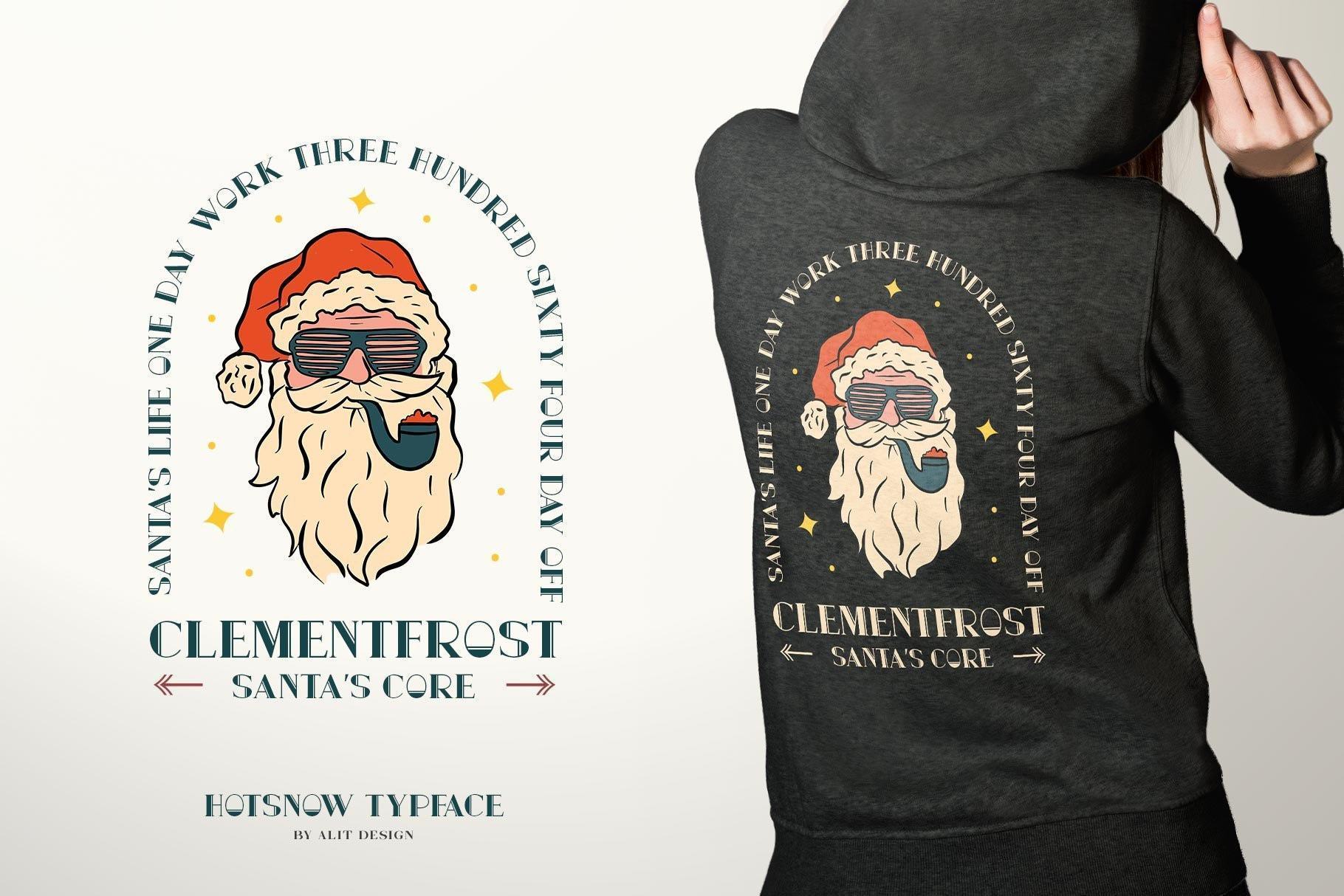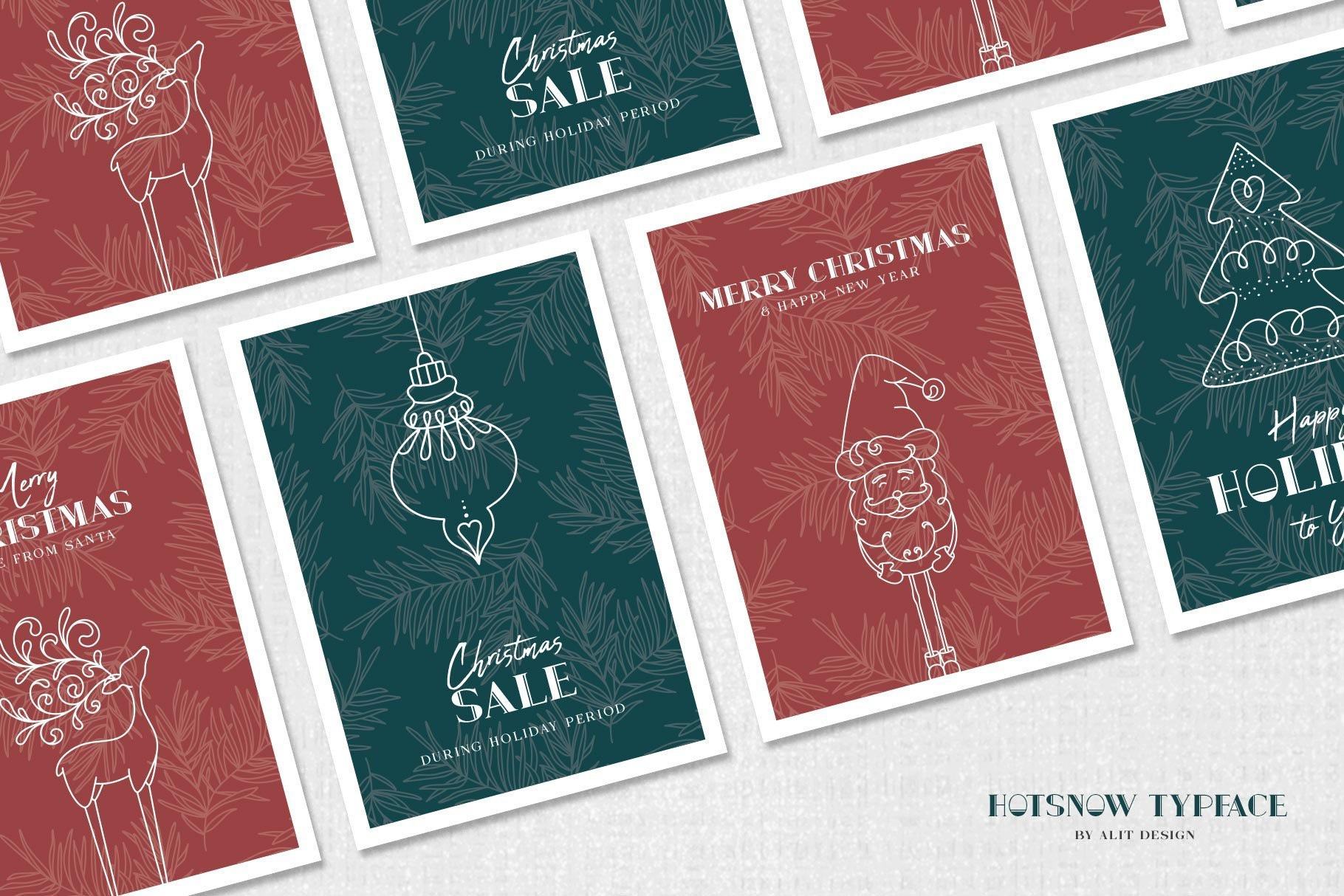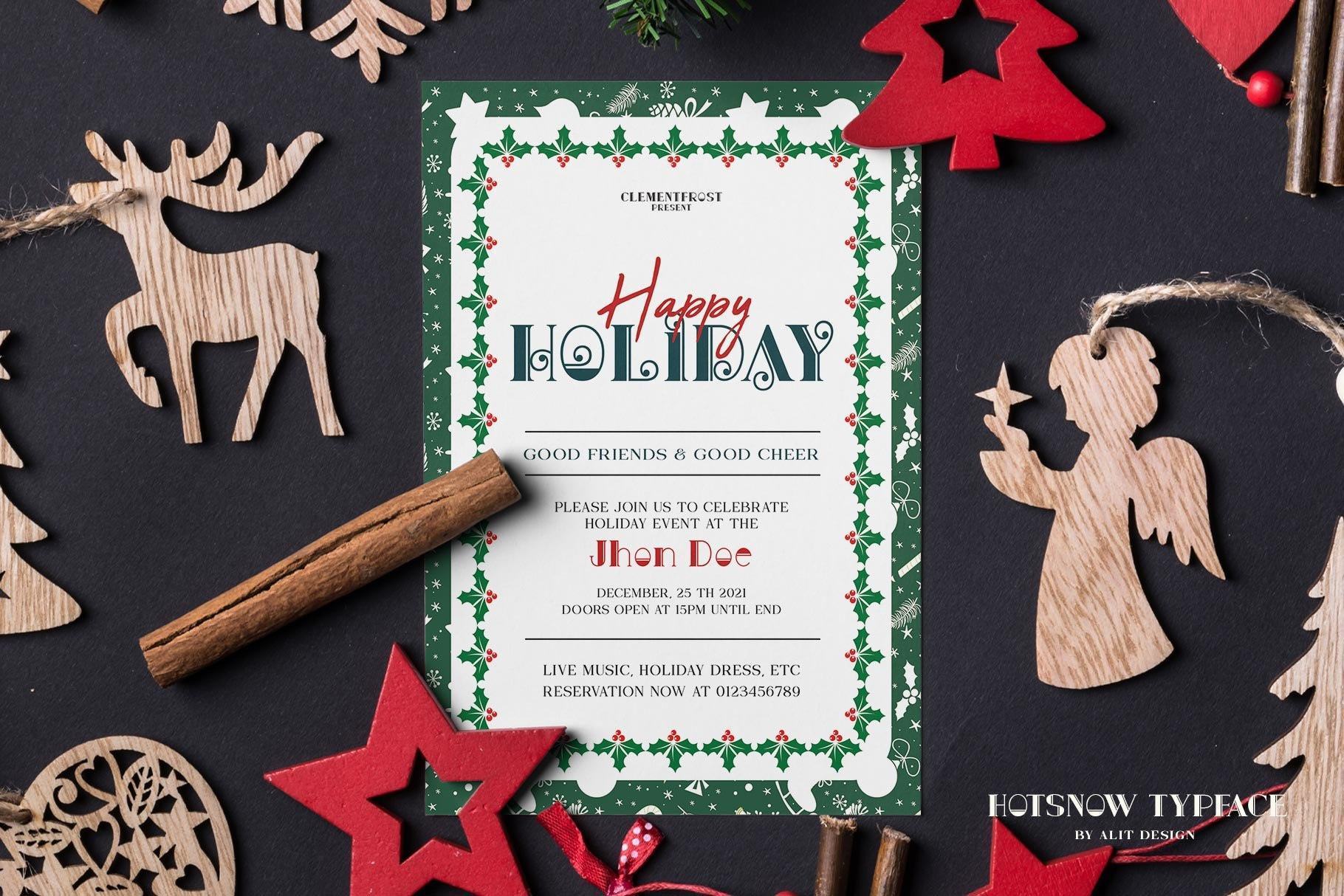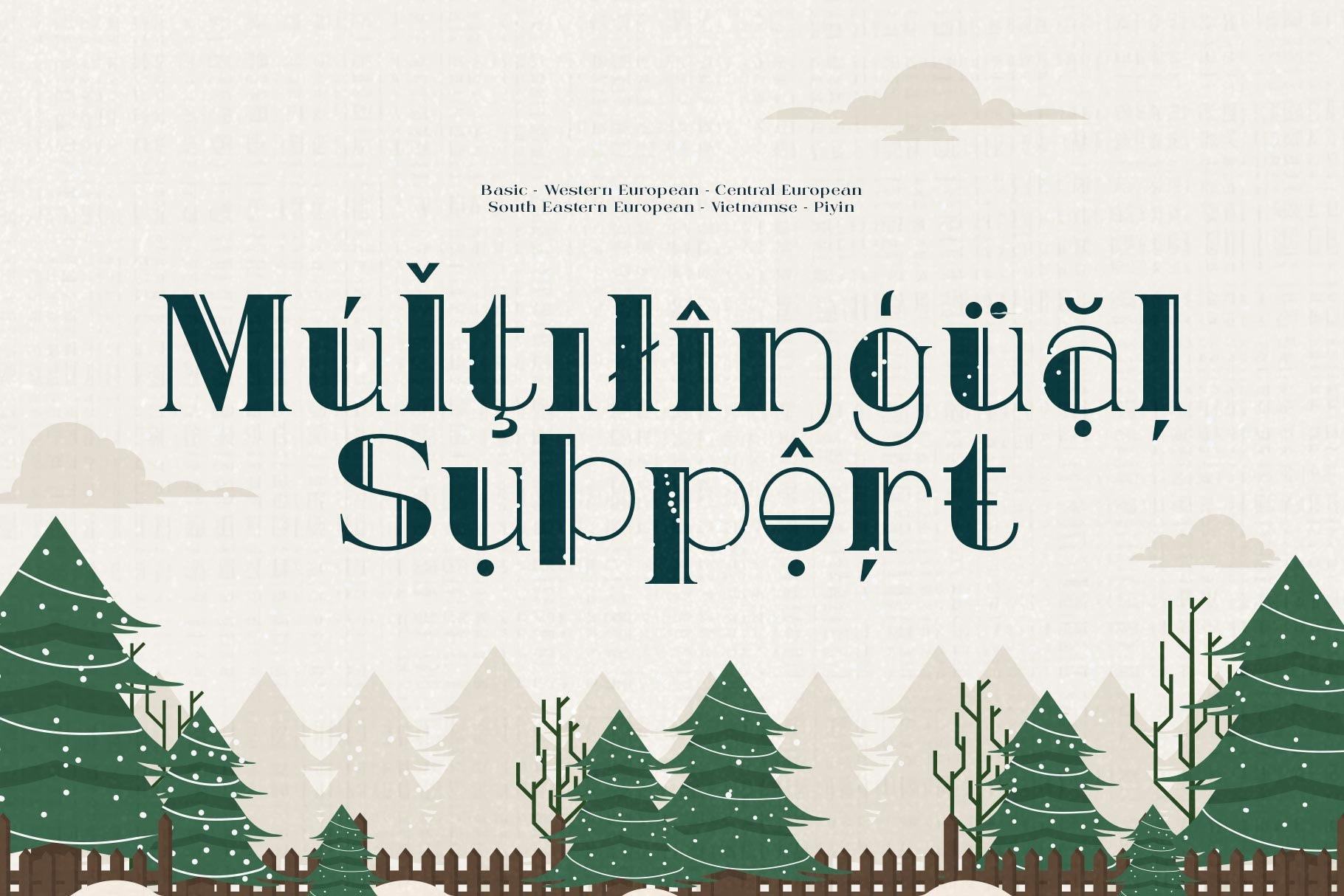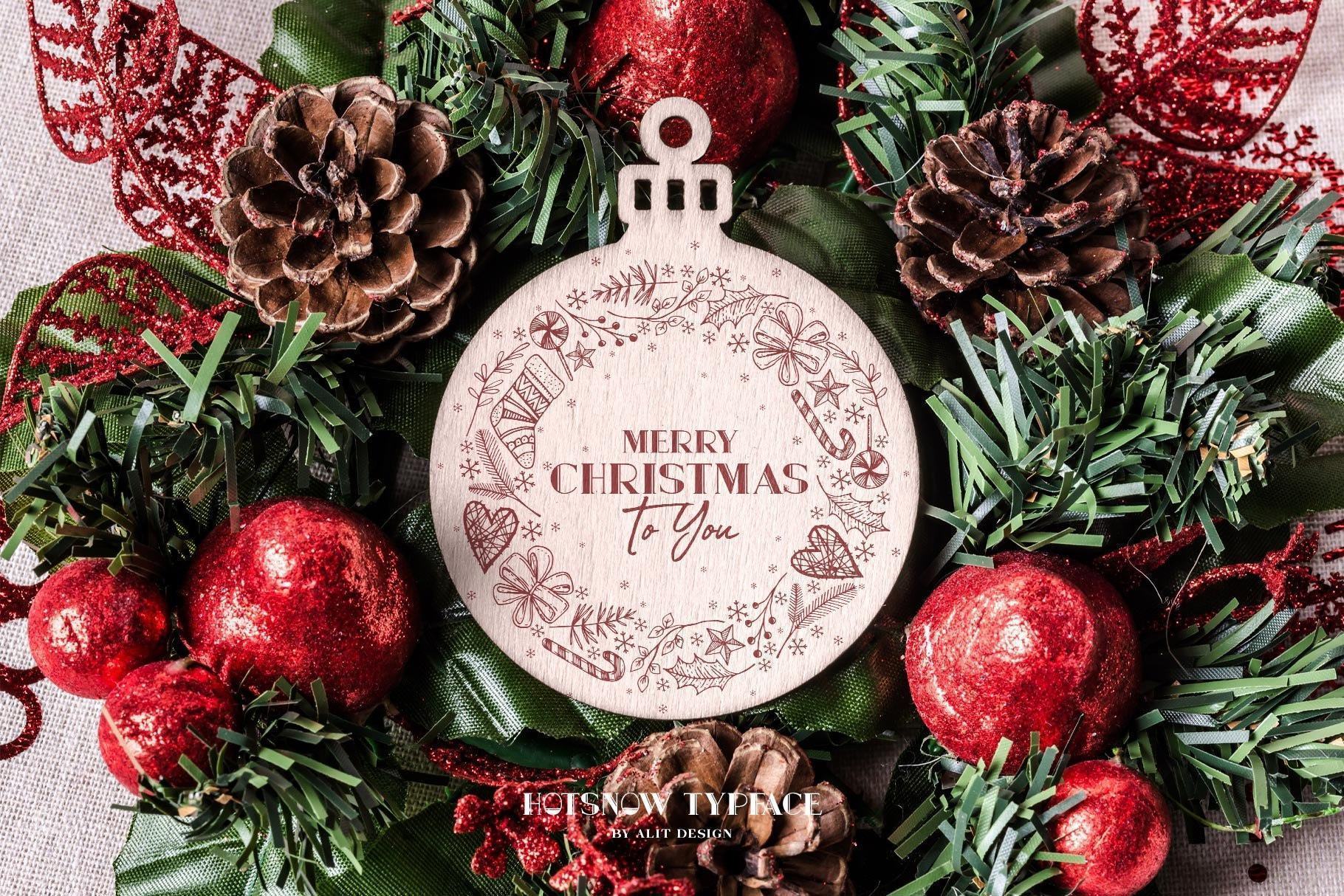
Hotsnow Font – Holiday là một bộ phông chữ được thiết kế đặc biệt để mang lại không khí lễ hội và ngày nghỉ. Với kiểu chữ độc đáo và đầy phong cách, Hotsnow Font – Holiday là lựa chọn hoàn hảo cho các dự án thiết kế đồ họa liên quan đến mùa lễ, kỳ nghỉ và sự kiện đặc biệt.
Phông chữ này mang trong mình sự vui tươi, tinh tế và độc đáo, giúp làm nổi bật và tạo điểm nhấn cho các thiết kế đồ họa. Sử dụng Hotsnow Font – Holiday, bạn có thể tạo ra các tiêu đề, bảng chú thích, thiệp mời, poster, hoặc bất kỳ tác phẩm nghệ thuật sáng tạo nào khác để thể hiện không khí lễ hội đầy sắc màu và vui nhộn.